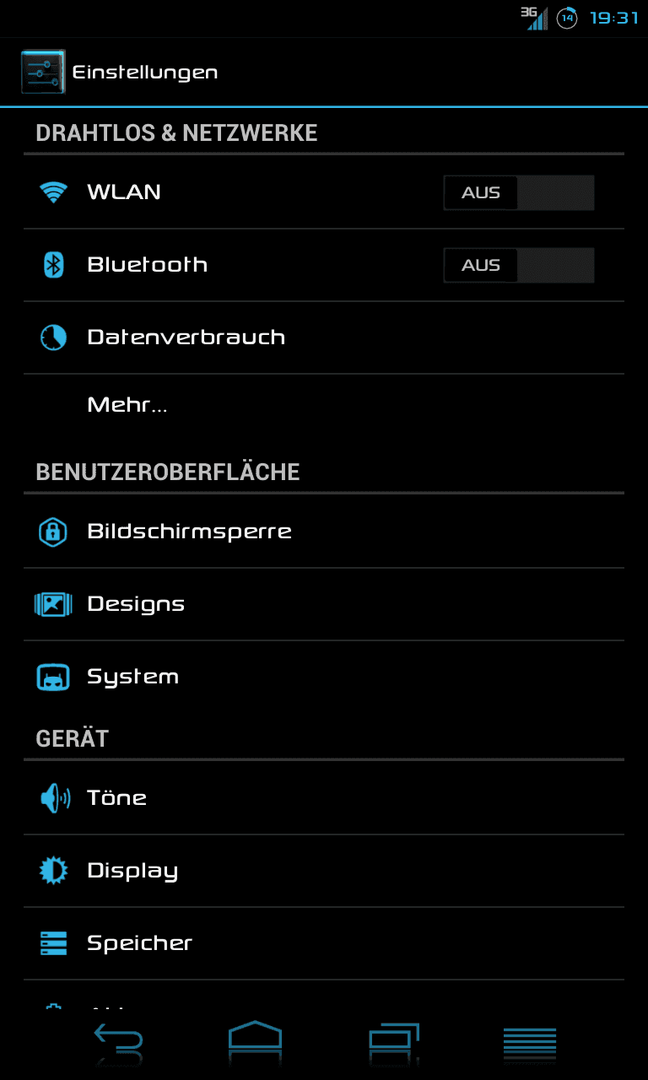
"Bester" Front-Schriftart für Nexus
Ich bin immer noch auf der Suche nach einem Schriftzug, der in Größe und Verhältnis zum Display , wie soll ich sagen :confused2: "nicht zu groß und nicht zu klein" ist. Sozusagen den "perfekten" Schriftzug.
Ich wollte mal fragen, mit welchen Schriftarten ihr so "unterwegs seid" ?
Ich verwende momentan diesen hier: "Dustimo"
Ich bin zB deshalb vom StockRom-Schriftzug gewechselt, da mir dieser oben in der Statusleiste einfach zu groß bzw "überdimensoniert" war. Das war natuerlich auch in vielen anderen Apps bzw Systemeinstellungen ähnlich.
Ich nutze die Comfortaa sieht super aus und die Schrift ist auch nicht zu groß oder zu klein
Ich verwende das Ubuntu font, stylisch und gut lesbar :)
Roboto ist doch immernoch gut :)
Beste Schriftart meiner Meinung nach: Sony Sketch
(begleitet mich seit ich Smartphones beseitze ;) )